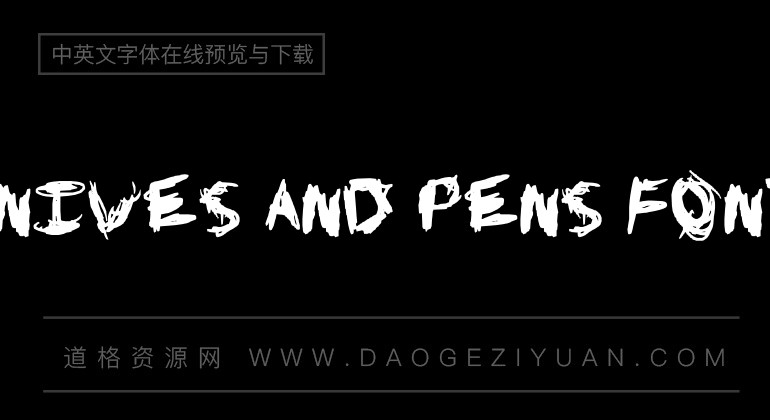
Knives and Pens Font
Knives and Pens 是一款英文字体,受到流行摇滚乐队 Black Veil Brides 的歌曲《Knives and Pens》的启发而设计。 该字体采用了粗体和锐利的线条,呈现出一种充满力量和动感的视觉效果。它的字母形状非常独特,每个字母都有明显的尖角和锋利的边缘,仿佛由刀刃和钢笔组合而成。 Knives and Pens 字体适用于设计海报、音乐专辑封面、标志、宣传册等需要突出个性和力量感的设计项目。该字体有多种风格和变体可供选择,支持多种语言和字体格式,非常适合设计师和创意人士使用。
Knives and Pens Font是一款非常不错的手写艺术字体,具有很好的视觉感,适合于文化类的宣传设计、商业类品牌的广告和产品包装设计以及个性化文字排版等较多场景。